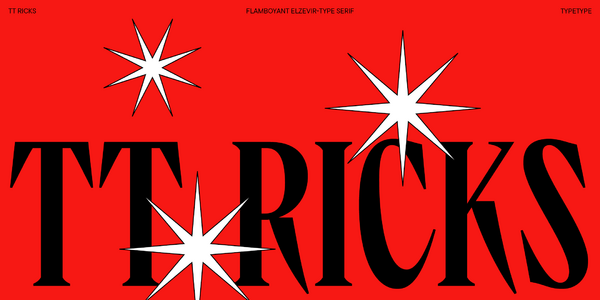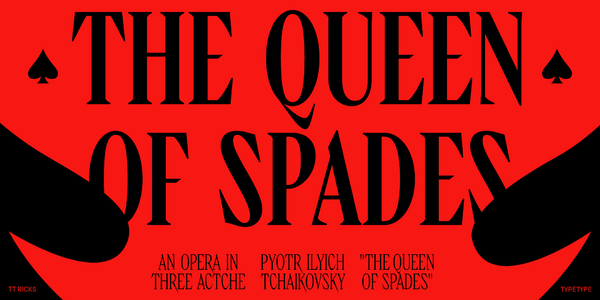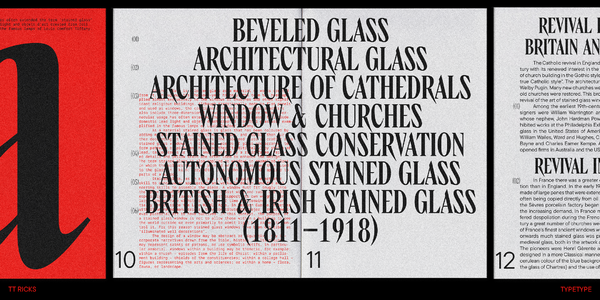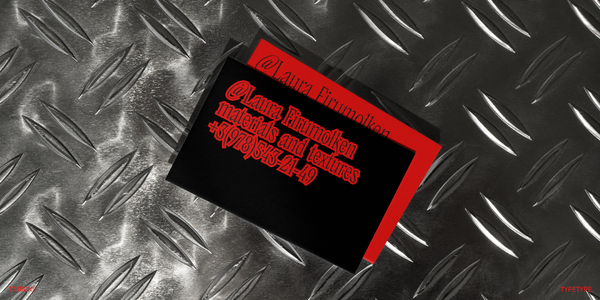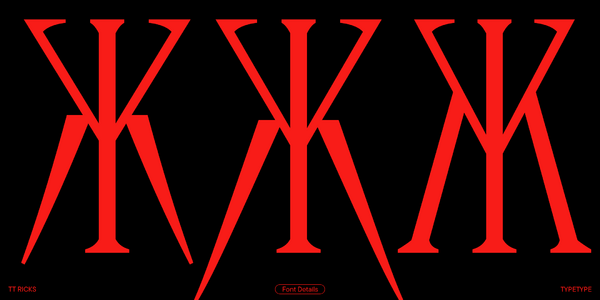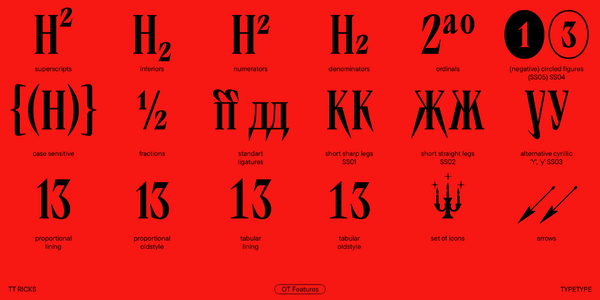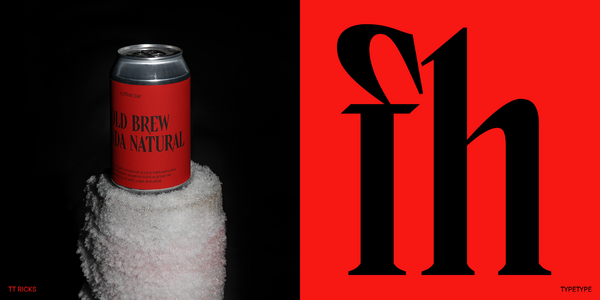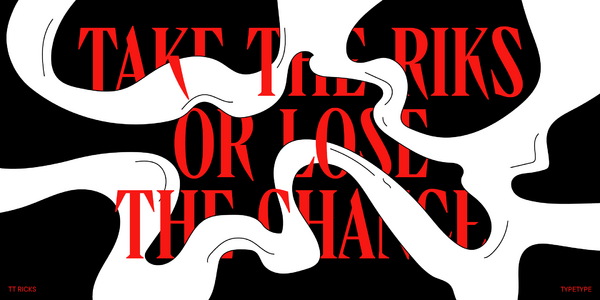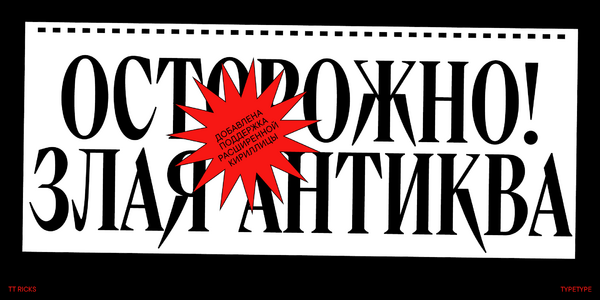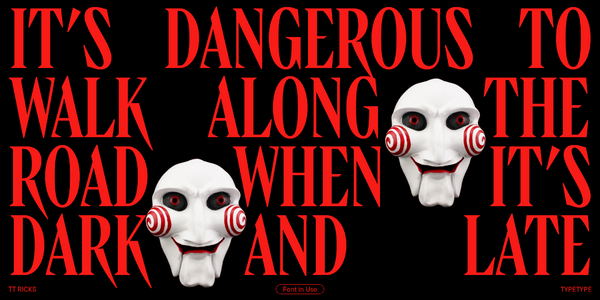
TT Ricks
TT Ricks — ТТ Рикс
Произносится «ТТ Рикс». «Ricks» — производное слово от rick, в переводе с английского «стог сена». Буквы «TT» являются аббревиатурой названия компании
TT Ricks — выразительная антиква с острым характером. Узкие формы, яркий контраст и колючие засечки, напоминающие шипы, делают шрифт дерзким и «злым».
TT Ricks is a flamboyant elzevir-type serif
The typeface is inspired by the pre-digital font «De Vinne», which was designed in 1892 by the designer Gustav F. Schroeder. We liked certain aspects of the historical prototype, but at the same time, when creating TT Ricks, we did not want to limit ourselves—on the contrary, we were eager to discover a completely new spirit and bring bright details to the font.
The TT Ricks typeface stands out for its strong contrast, noticeable sharp serifs, narrow letterforms
Встречайте TT Ricks в новом воплощении — теперь с поддержкой кириллицы!
Значительно расширили кассовый состав, обновили кернинг и хинтинг, добавили новые OpenType фичи и стилистические сеты.
TT Ricks — выразительная антиква с острым характером. Создавая ее, мы вдохновлялись шрифтом De Vinne, разработанным Густавом Шредером в 1892 году. Мы сохранили некоторые аспекты исторического прототипа, но при этом не ограничивали себя стилистическими рамками. Напротив, нам хотелось привнести в TT Ricks неожиданные детали и наделить его абсолютно новым духом.
Характерные черты TT Ricks — сильный контраст, очень плотный спейсинг, узкие формы знаков и своеобразные засечки, напоминающие шипы. В нем множество интересных деталей: например, наклон овалов у круглых букв («с», «е», «s»), характерные строчные знаки в латинице, несимметричные ноги у «Дд», «Цц». Это «злая» антиква, которая, впрочем, иногда усмиряет свой дерзкий нрав: в регулярном начертании она резкая и колючая, а в жирном становится более основательной, приобретая готические черты.
В обновленной версии мы полностью обновили кернинг и доработали хинтинг. Добавили кириллицу и дополнили латиницу. Расширили основной набор валют, а также дорисовали минускульные валюты, включая табулярные валюты для обоих регистров. Нарисовали дроби и цифры для нумераторов и денумераторов, добавили цифры в кружочках. Кроме того, в TT Ricks версии 2.000 появились новые стилистические сеты для кириллицы. А сет авторских иконок расширяет возможности применения и еще больше раскрывает характер гарнитуры.
TT Ricks лучше всего работает в среднем и крупном размерах, сразу привлекая к себе внимание. Этот шрифт отлично подходит для дизайна упаковки, книжной графики, оформления постеров и афиш.
Обновленная версия TT Ricks — это:
• 4 начертания: 3 прямых и 1 вариативный шрифт;
• 1009 глифов в каждом начертании;
• 31 OpenType фича, в том числе возможность менять некоторые знаки на альтернативные;
• Поддержка более 230 языков, в том числе локализации для болгарского, сербского, чувашского и башкирского.
Что изменилось в шрифте:
• Значительно увеличился кассовый состав: с 553 до 1009 знаков;
• Добавились новые OpenType фичи: их количество выросло с 18 до 31;
• Появилась кириллица, дополнилась латиница;
• Выросло количество поддерживаемых языков — со 175 до 230;
• Полностью обновился кернинг — мы улучшили и расширили его;
• Обновился хинтинг для всех знаков — его мы доработали и усовершенствовали;
• Расширился основной набор валют, появились минускульные валюты (включая табулярные валюты для обоих регистров). Также появились дроби, цифры для нумераторов и денумераторов;
• Появились новые стилистические сеты для кириллицы.